Sven Neumann hat an der HTW Berlin im Fachbereich Gestaltung in diesem Jahr ein empirische Untersuchung zur Leserlichkeit von von Schrift im öffentlichen Raum durchgeführt. Die durch Prof. Florian Adler betreute Studie basierte in Bezug auf Schriftgrößen und Leseentfernung auf den Vorgaben der Norm DIN 1450 und spiegelt somit reale und empfehlenswerte Bedingungen beim Lesen von Schildern und Texten im öffentlichen Raum wider.
Versuchsbedinungen: Am Test nahmen 106 Personen unterschiedlichsten Alters teil. Die Testpersonen näherte sich in festen Abständen den Schriftmustern an. Bei einer als ausreichend gut empfundenen Lesbarkeit wurden die jeweiligen Leseentfernungen notiert. Vorab wurden Alter und weitere Angaben (Sehhilfe etc.) zu den Probanden erfasst.
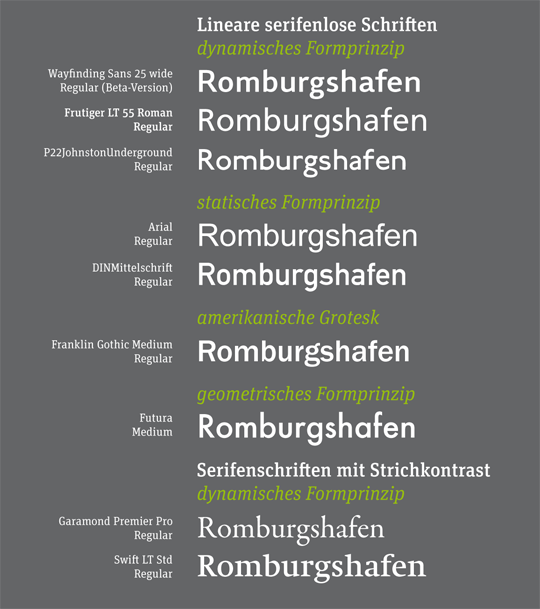
Getestet wurden zwei Schriftgrößen mit fiktiven Einzelwörtern sowie ein Fließtext in kurzer Distanz. Da sich die Empfehlungen der aktuell noch gültigen DIN 1450 lediglich auf die Versalhöhe beziehen, wurde eine zweite Versuchsanordnung benutzt, bei der alle Wörter auf die durchschnittliche x-Höhe der benutzten Schriften skaliert wurden.
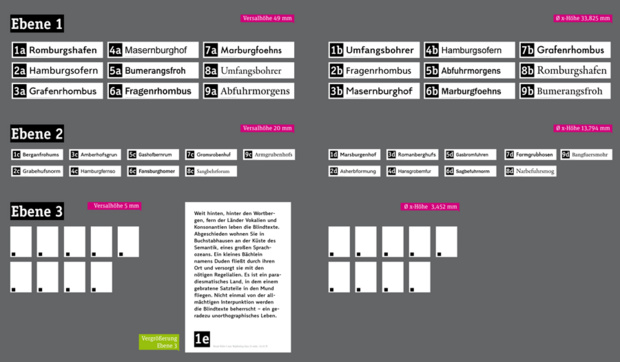
Dieser Versuchsaufbau hebt sich in zweierlei Hinsicht von vielen wissenschaftlichen Vergleichsstudien zur Leserlichkeit einzelner Schriften ab. Zum einen wurde nicht der typische Fehler begangen, die Schriften lediglich in gleicher Kegelgröße zu setzen. Des weiteren erfolgte der Test mit Wörtern und nicht, wie bei vielen wissenschaftlichen Studien üblich, nur mit Einzelbuchstaben.
Getestet wurden die aufrechten Schnitte der Linotype Frutiger, P22 Johnston Underground, Wayfinding Sans, Arial, DIN1451 Mittelschrift, Franklin Gothic Medium, Futura, Garamond Premier Pro sowie die Swift.
Ergebnisse: Klarer Gewinner der Studie ist die derzeit noch unveröffentlichte Wayfinding Sans von Ralf Herrmann, die in einer Beta-Version getestet wurde. »Im Test konnte die Schrift im Vergleich zu allen anderen Schriften in allen Größen früher gelesen werden« schreibt Sven Neumann in seinem Abschlussbericht. Sie ist nicht nur deutlich früher lesbar als die DIN 1451 Mittelschrift, die auf deutschen Verkehrsschildern benutzt wird, sondern überflügelt sogar die Frutiger, die als die Beschilderungsschrift schlechthin gilt und zum Beispiel der Standard im Bereich Flughafenbeschilderungen ist.
Die Frutiger schneidet aber ansonsten erwartungsgemäß sehr gut ab. Mit ihren klaren Grotesk-Formen schuf Adrian Frutiger mehr oder weniger den Archetypen moderner humanistischer Groteskschriften. Ebenfalls gut schnitt die Johnston Underground ab, an die man nicht unbedingt sofort denkt, wenn es um Beschilderungen geht. Die getestete Version ist eine Digitalisierung von P22. Das Original wurde ursprünglich für die Beschilderung der Londoner Verkehrsbetriebe entwickelt. Der typisch britische Charakter vereint klare geometrische Formen mit humanistischen Zügen, die sich zum Beispiel im zweistöckigen a und dem dreistöckigen g zeigen.
Im Mittelfeld landen Arial, DIN 1451 Mittelschrift und Franklin Gothic Medium. Im Gegensatz zu oben genannten Schriften sind sie statischer und geschlossener und fallen deshalb in diesem Test spürbar zurück. Wenig überraschend ist sicherlich auch, dass die Futura im Test mit identischen Versalhöhen noch schlechter abschneidet. Mit ihrem stark geometrischen Aufbau und der geringen x-Höhe kann sie mit den eher humanistischen Groteskschriften in Bezug auf die Leserlichkeit nicht mithalten.
Die Serifen-Schriften Garamond Premier Pro und Swift erzielen erwartungsgemäß ebenfalls keine guten Ergebnisse, wenn alle Schriften mit gleicher Versalhöhe gesetzt werden. Dies liegt weniger an ihrem generellen Gestaltungsprinzip, sondern neben der geringeren x-Höhe auch an ihrem Duktus. Der im Vergleich zu den Groteskschriften starke Strichstärkenkontrast erfordert optimale Lesebedingungen, wie man sie nur bei Drucksachen in typischen Leseentfernungen vorfindet. Bei einem ungünstigen Verhältnis von Schriftgröße und Leseabstand sind die filigranen Details und Haarlinien nicht klar genug zu erkennen und die Leserlichkeit nimmt spürbar ab.
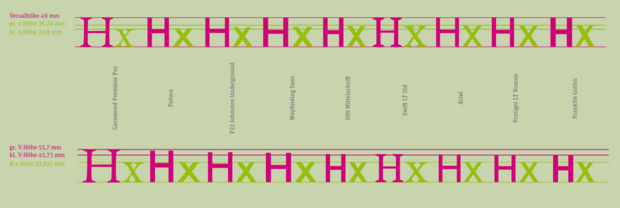
Da der Versuch einmal mit identischer x-Höhe und einmal mit identischer Versalhöhe durchgeführt wurde, ist einer Vergleich der beiden Ergebnisse natürlich besonders interessant. Die Wayfinding Sans und die Johnston Underground haben mit ihrer x-Höhe zwischen 67 und 69 Prozent das perfekte Mittelmaß gefunden und schneiden in beiden Tests gleichermaßen gut ab. Die Schriften mit kleinerer x-Höhe können nur durch eine deutliche Anhebung des Schriftgrades leserlicher dargestellt werden. Dies führt aber verständlicherweise zu einem sehr hohen vertikalen Platzbedarf, der gerade bei Beschilderungen oft nicht gegeben oder sinnvoll ist. Denn sobald die Ober- und Unterlängen mit anderen Zeilen oder Umrandungen in Konflikt geraten, verschlechtert dies die Leserlichkeit wieder beträchtlich.
Die Schriften mit einer größeren x-Höhe schneiden bei beschränkten vertikalen Platzbedarf wenig überraschend besser ab – allerdings auch nur dann. Spielt der Platz keine Rolle und haben alle Schriften die gleiche x-Höhe schneiden Garamond und Futura erstaunlicherweise sogar besser ab als Frutiger, DIN 1450 und Arial.
Am Beispiel der Schriften (Versalhöhe 49 mm) wird deutlich, dass nicht nur die Schriftart die Leserlichkeit einer Schrift beeinflusst. Der Vergleich der einzelnen Altersgruppen zeigt erwartungsgemäß eine eindeutige Tendenz. So haben die Teilnehmer im Test in der Altersgruppe bis 15 Jahre am besten und die Gruppe über 60 am schlechtesten abgeschnitten. Durchschnittlich gibt es eine Differenz zwischen höchster und niedrigster Leseentfernung von 4,95 Metern.